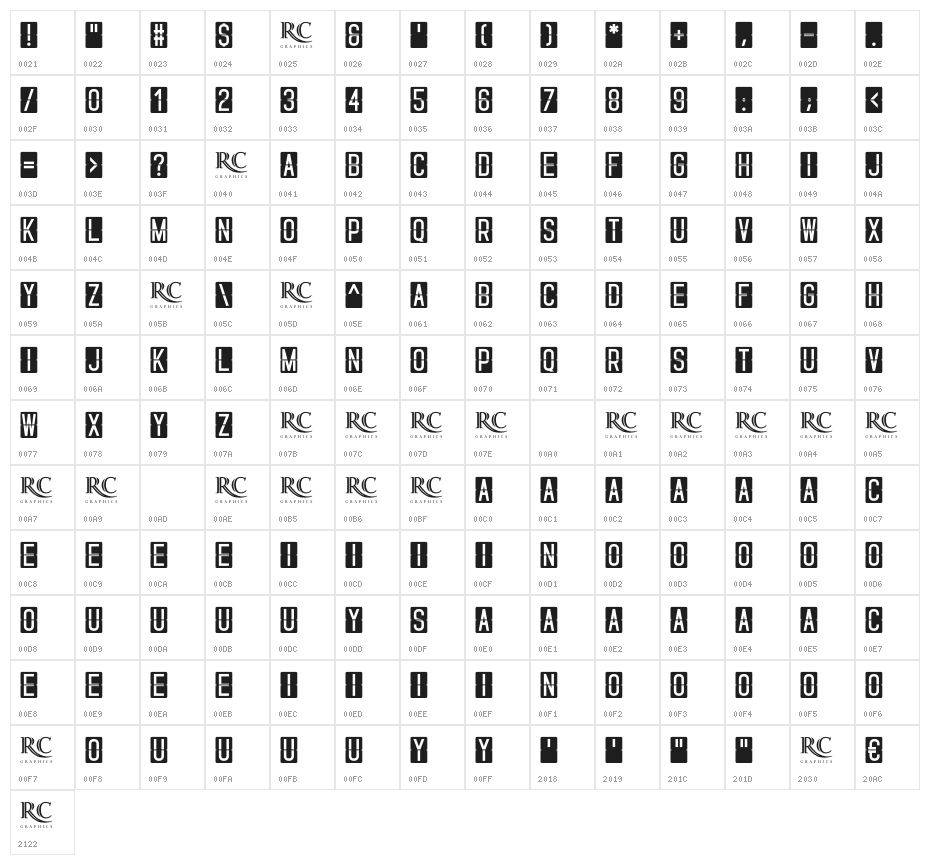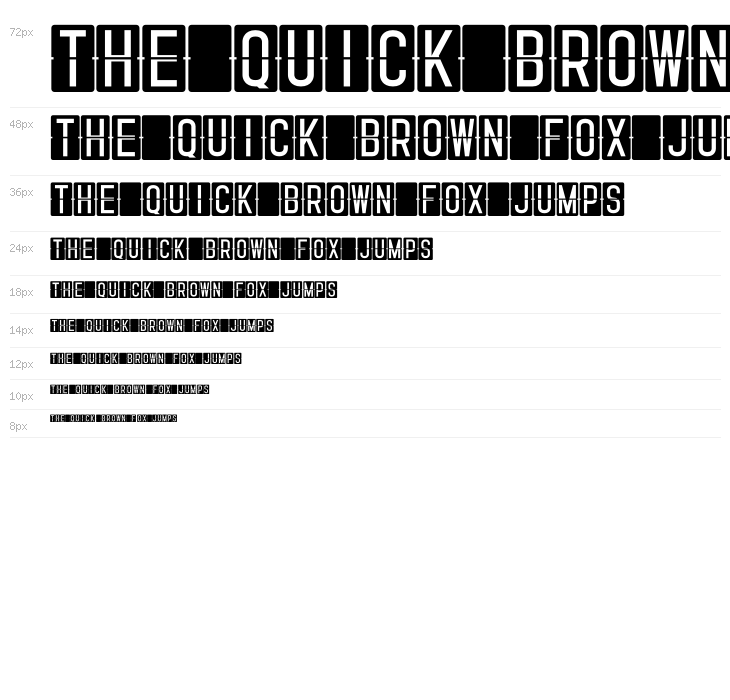
Skyfont Font
✎ Sans Serif
| 分类 | Sans Serif |
| 整体风格 | Vintage |
| 推荐项目 | Ideal for retro-themed posters, branding, signage, and any project needing a vintage yet modern touch. |